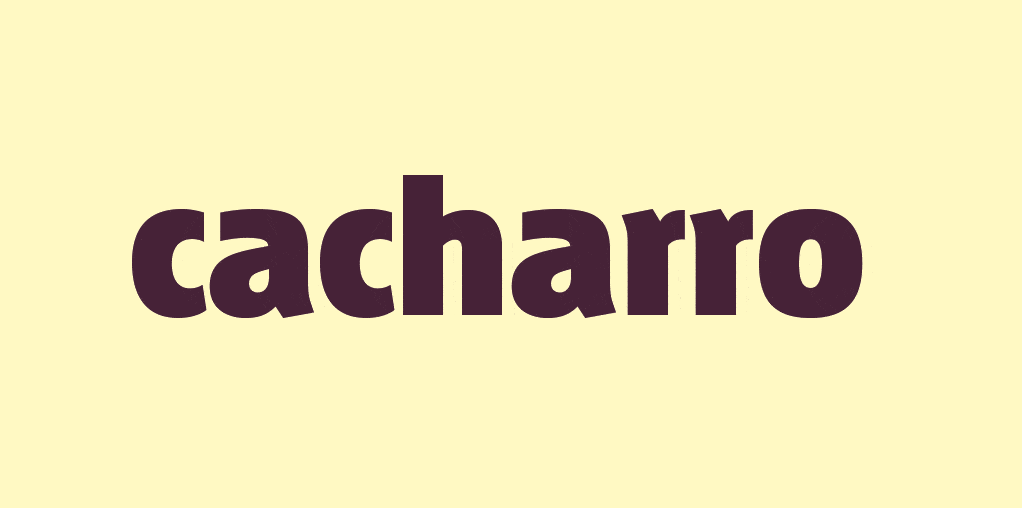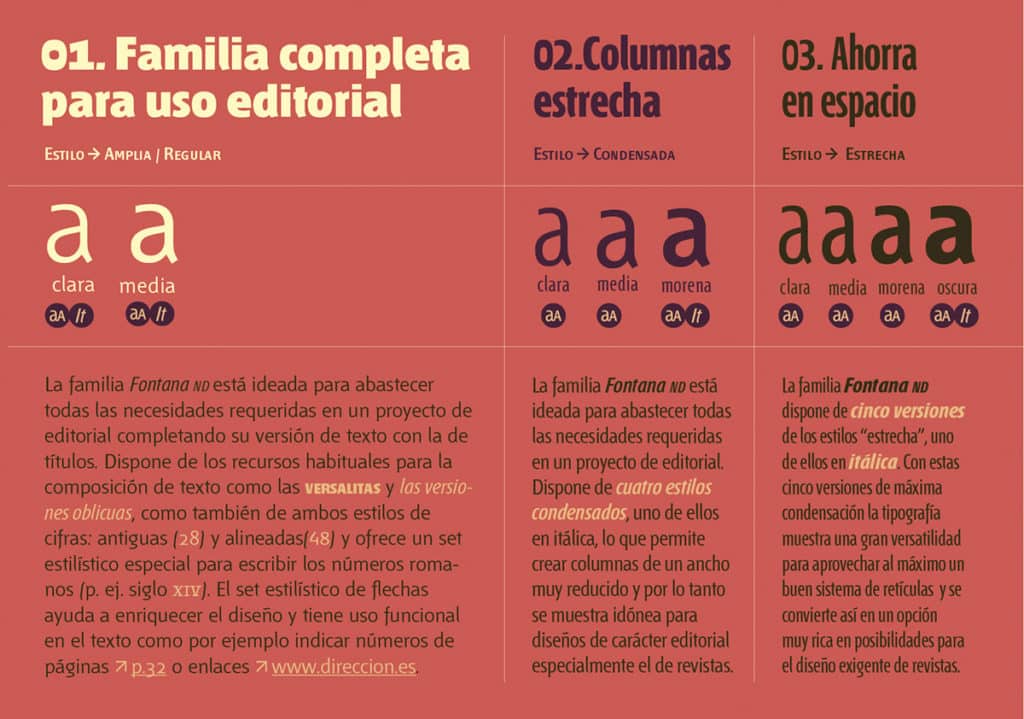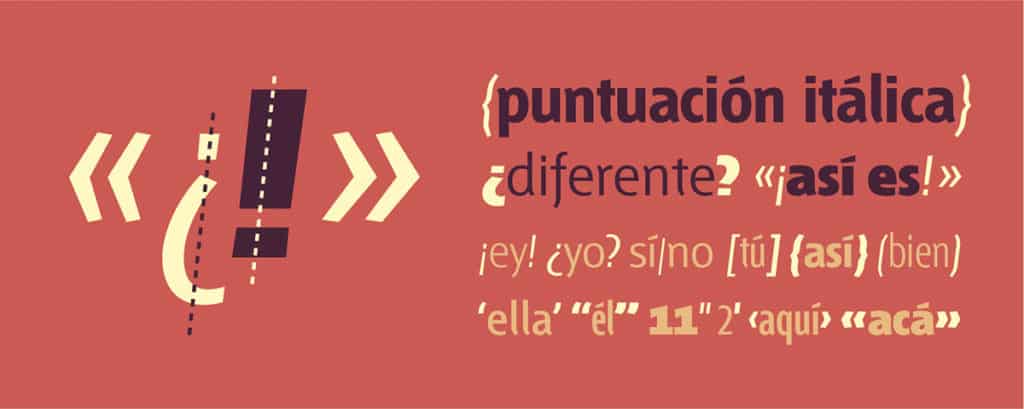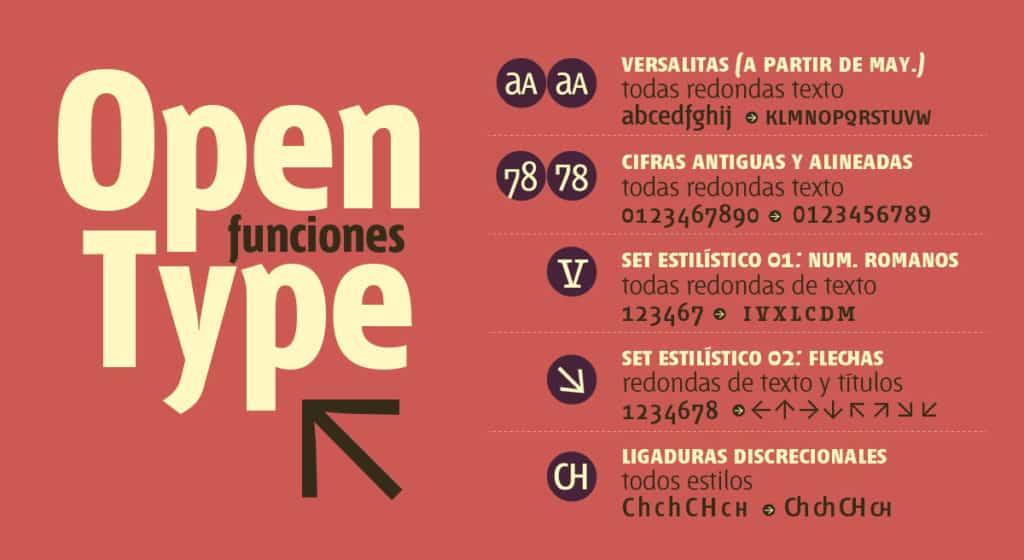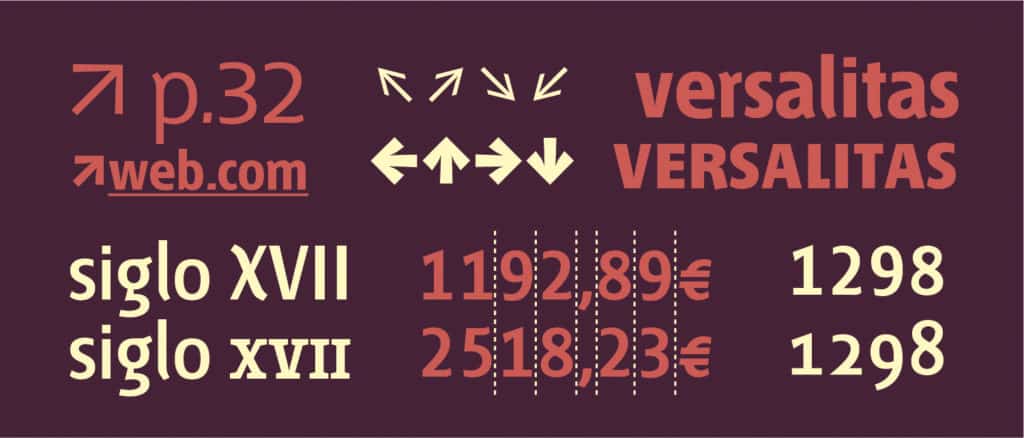
Como os hemos contado en el anterior artículo, Fontana ND fue diseñada por Rubén Fontana para la revista tipoGráfica. Queremos ahora destacar sus particularidades y las funciones OpenType que permiten sacar el máximo partido:
Fontana ND tiene tres características principales que la distinguen: el particular sistema de variaciones de estilo que conforma la familia, el contexto de la lengua española y el uso editorial.
CONTEXTO DE LA LENGUA ESPAÑOLA
El contexto del castellano es importante en los diseños tipográficos de Rubén Fontana. Esto se refleja especialmente en las ligaduras discrecionales creadas para enfatizar el dígrafo «ch» particular de nuestra lengua. En Andralis ND este énfasis es más pronunciado, al crear ligaduras especiales también para los pares de letras «qu» y «rr». Mediante la opción OpenType de “ligadura discrecional” podemos aplicar la unión entre las letras c y h para crear así un único signo ligado. En nuestra cadena de post Open your Mind, Open your Type os contamos en detalle cómo hacerlo utilizando las herramientas OpenType en los programas Illustrator e InDesign.
SISTEMA FONTANA
El contexto de la lengua española también se ve reflejado en el sistema de Fontana en el que los distintos pesos (desde light hasta heavy) se llaman clara, media, morena, oscura y ultra. Y los distintos anchos (regular, condensed y compressed) se distinguen como amplia, condensada y estrecha. La familia está ideada para abastecer todas las necesidades requeridas en un proyecto de editorial sumando a sus 13 estilos de texto otros 8 para títulos. Este sistema resulta de la evaluación de uso en la publicación para la que fue diseñada la letra. Por consecuencia no todas las variaciones de peso están presentes en las distintas versiones de ancho ni tampoco hay una equivalencia de oblicua para cada versión redonda (tan sólo tiene 5 versiones itálicas). Como peculiaridad adicional, todos los signos de puntuación son oblicuos en todos los estilos.
USO EDITORIAL
Este sistema que presenta tres variaciones de ancho es también un reflejo del uso para el que fue concebida ya que permite ahorrar espacio, aprovechar al máximo un buen sistema de retículas y se convierte así en un opción muy rica en posibilidades para un diseño editorial exigente. Dispone de los recursos habituales para la composición de texto como las versalitas y las versiones oblicuas, como también de ambos estilos de cifras: antiguas y alineadas (su ancho es tabular en ambas versiones) y ofrece un set estilístico especial para escribir los números romanos (p. ej. siglo XIV). El set estilístico de flechas ayuda a enriquecer el diseño y tiene uso funcional en el texto como por ejemplo indicar números de páginas o enlaces.
Gracias a todas estas particularidades y prestaciones OpenType, Fontana ND se convierte en una tipografía versátil a la que poder sacar máximo partido en diseño editorial.